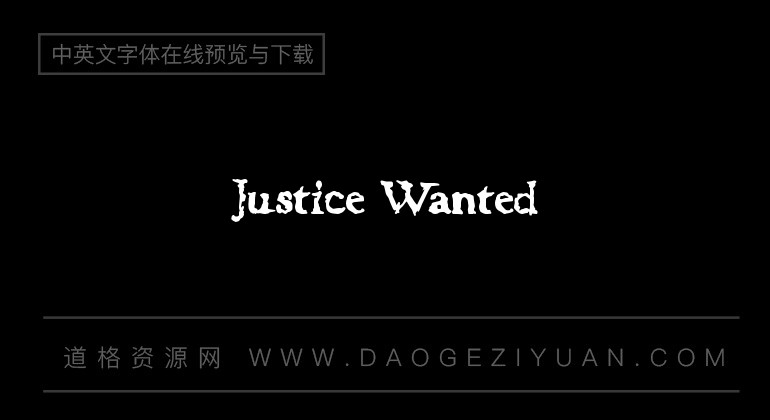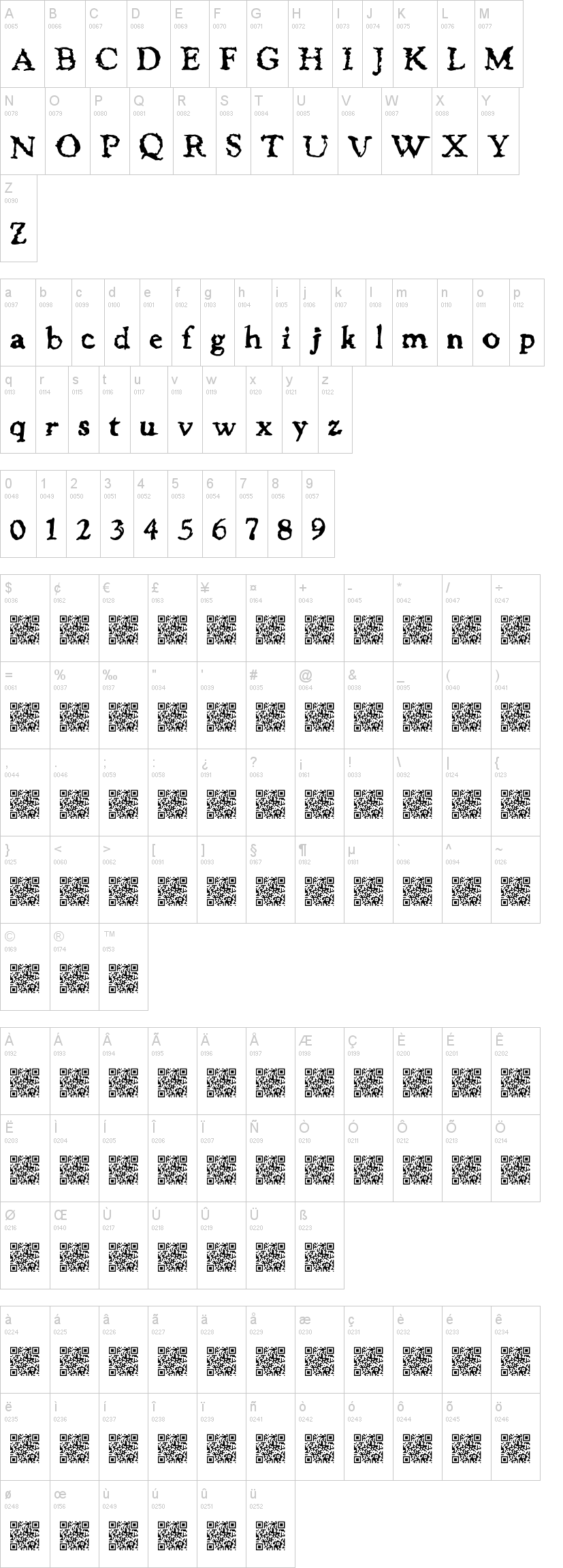
Justice Wanted 字体是一款漂亮的手写体字体,它具有朴实、简洁的特点。它适合用于标题、标签、标语、介绍、广告等文字内容。Justice Wanted 字体具有良好的可读性,可以让文字内容更加清晰易读。它的设计灵感来自于自然界中的生物,可以让文字内容更加有趣。内容介绍
Justice Wanted是一款非常不错的手写艺术字体,具有很好的视觉感,适合于文化类的宣传设计、商业类品牌的广告和产品包装设计以及个性化文字排版等较多场景。